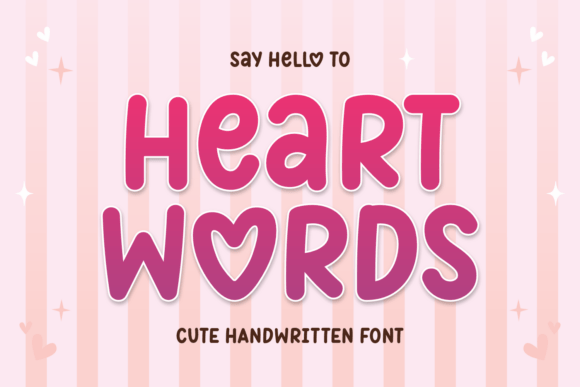
Heart Words
Wenn Sie nach hochwertigen Assets wie Heart Words suchen, ist dieses Premium-Paket eine fantastische Wahl für Ihre kreativen Projekte.
Mit Präzision gefertigt, bietet Heart Words saubere Vektoren, eine reibungslose Typografie und eine kommerzielle Lizenz für ein beruhigendes Gefühl.
Egal, ob Sie POD-Produkte (Print on Demand), Hochzeitseinladungen oder Social-Media-Grafiken erstellen, Heart Words ist die ideale Wahl.